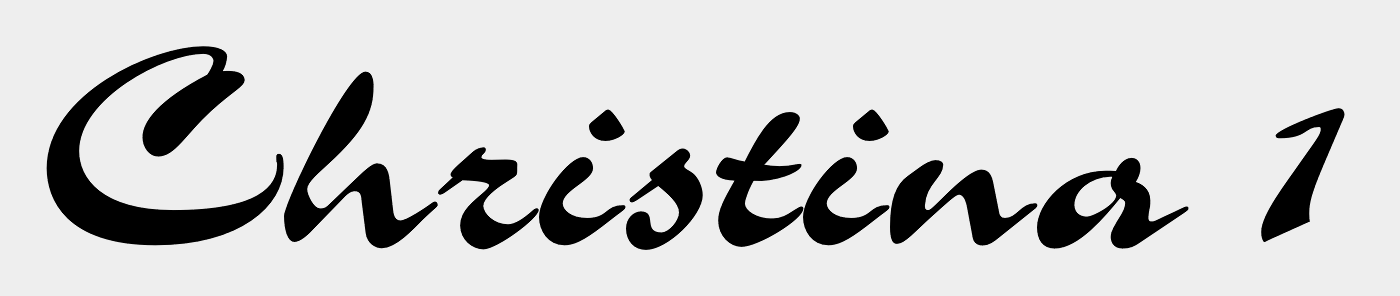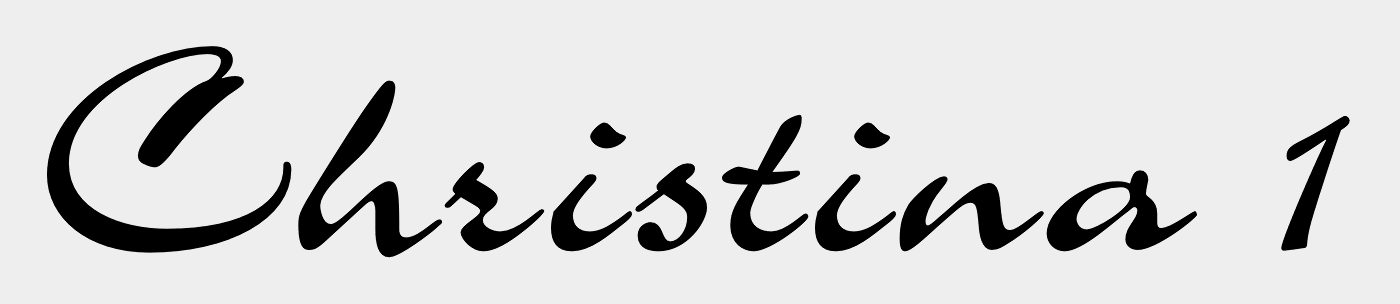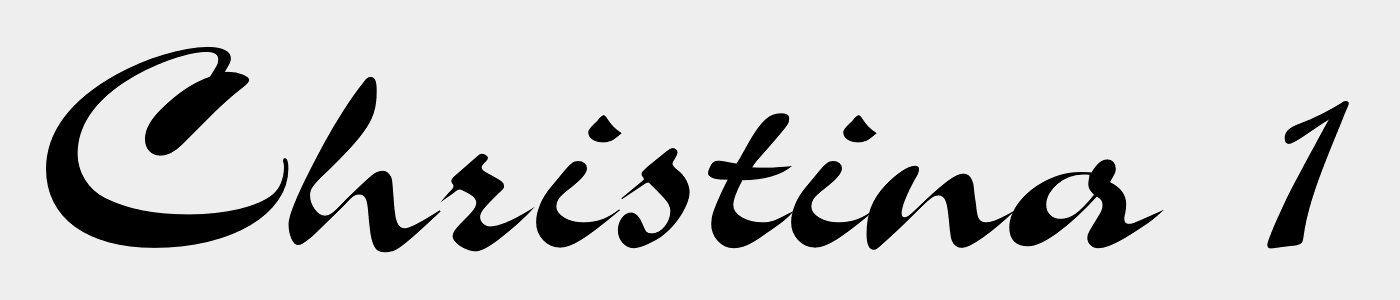
schriftname gesucht
Wenn die Bootsbeschriftung (?) angelegt wird, bitte darauf achten, dass die Verbindungen der Buchstaben sauber ausgeführt werden, nicht dass das fertige Ergebnis wie in den Vorschau aussieht :-o. Das erfordert ein wenig Handarbeit, ist die Sache aber wert.